中外字体之检讨
印刷到现在已有惊人的发展,但是无论其发展至何种境地,检讨其方向总跳不出两条道路:(一)美观;(二)速度。此两种方向印刷界是永无休止的迈进着。
欲使版面美观,除去排列之技巧新颖外,并且还须不同的字体陪衬着。这里,把中外之字体检讨一下。
中国字体
现在大部分之书籍与报纸上之文章,所用的字为明体。这种字体为正方形字体,大小均匀,印出十分的整齐。其名称之来源,大概因此体为明时所通用之一种体格。
宋体,此为宋时流行的一种字体,故名之宋体。此种字体用于印刷上,约有十五年之历史。最早的一副铜模,乃中华书局所制,当时会请求实业部专利。后来大家见其字体印出十分好看,所以仿制起来。在北平樱桃斜街有一家文岚簃即亦制了一副,因此会与中华书局打了一场官司,结果获胜。此体又分两种:长方体;正方体。现在此种字体太多了,与普通的明体一样,也谈不到专利了。并因有楷体之出现,亦为之减色不少。
清体即楷书,虽不始于清,但清时用此种字体者最为普遍。考八股文时即须用此体。所谓工楷者,即此体也。书报上用楷书,乃为最近之事,并不普遍。民国二十一年,有一汉文正楷印书局,他首创一副正楷铜模。(单个)他的目的是印书,但也出售铅字。他亦请实业部准予专利,不准他人偷制。他这买卖做了许多年,至如今北平有永兴洋纸行,所出售之正楷铅字,仍为此模制出。今上海有华丰铸字所也制一副。此外,还有姚姓者也制一副。(成功否未明)以上为中国自己创制之铅字铜模。除此之外,日本有大普公司,也出有正楷铜模,(集合铜模,万能铸字机所用)并且号数齐全。他的性质与中国各家不同。中国各家是专售铅字,而不出售铜模;大普公司是出售铜模。现今北平世界日报即有此种铜模,为大普公司所出之头一批。
隶书与行书这两种,中国尚无铜模;书报上虽有见到,亦是刻出的。在日本已有用的了。
以上的五种字体,都为中国固有的几种体材。现在又由西方传过一种体材:黑体(Gothic Style),为罗马所发明。如今的建筑物讲求立体式;把立体式之建筑放在字体上,即为黑体。黑体字印在书报上,十分的醒目。这种黑体之笔画是方形的。现在日本又有一种圆笔画的发明。所以黑体又分两种:「方笔道」,「圆笔道」。
中国之字体大概分上述几种,除去尚没有用到的字体之外,可分成下面的样子:
中国字体之分析表:
- 用处最多的——明体
- 印出美丽的——
- 清体
- 宋体
- 适合标题的——黑体
西洋字体
西洋字体,最普通的有「罗马体」(Roman),此种可以等于中国如今之「明体」。其次有「意大利体」(Italic),即在书报上常见之斜体的草书。凡是一个固定的名词,或是要使人注意的文字,都用此种意大利体,因其醒目美丽。除此以外,还有其他各种,就多得不可思议了。可用中国「花字」之名称代替之。英文称这些字为 “Job Types”,为零碎之意。外国所以有这许多种字体之原因,是因为外国只有二十六个字母,所以铜模也容易制,不像中国每副铜模须数千个而还不敷用。既如此,外国的每一个印刷所,要表现他的外观,即另创一种字体,制一副铜模。但外国虽然有这许多字体,其通常所用的仍是罗马体与意大利体,为的是能够统一。所以,外国的字体可说是一面求美丽,一面求统一。
广告和现代印刷术(一)
一、广告和印刷术的关系
现代的广告品,大部份是要经过印刷的。美国每年全国广告的费用,百分之五十以上,是刊登于报纸和杂志上的广告;其他如招贴、传单、手册等,几无一不借印刷,其支配于其他广告媒介物,为数较少。因为报纸和杂志传佈广告者所要发表的消息,迅速而又普遍,所以能成为广告最主要的媒介物。这种媒介物既须通过印刷,所以广告制作者对于印刷的基本知识,非有相当的瞭解不可。如果我们对于广告实务上的知识,缺乏经验,所作成的广告稿本,当然不能臻于完善。现代规模较大的公司中,设有广告部,广告员多系分工从事,在一般人看来,似乎设计者不必要有绘图的知识,更不必要有印刷上的知识;但实际上,如果没有绘图和印刷知识的人,来计划制作广告,其结果必归于失败,是没有疑问的。这正和建筑师一样,虽然不必要自己动手来建造房屋,但是他在打样的时候,对于房屋内部的构造,材料的支配,必先有全部的知识和通盘的计划,才能使各匠工尽其所能。所以广告制作者对于印刷知识的重要,不可言之。兹略述印刷源流及基本印刷知识于后,以供参考。
二、中文活字
中文活字的沿革
印刷术为我国三大发明之一,启现代文化之端。现代文化是赖活字而产生的,赖活字而向上发达,印刷术实成为文化的一大因子。现代人一日不能离活字而生活,自每日阅读的报纸、杂志以至一切印刷物,其有关文字者,几无不利用活字而成。活字实具有表示意志、支配思想、记录日常所发生的事情之重大职能,这种活字是经过了种种的阶段,才成为现在我们所用的金属活字。
我国印刷术的发明,居各国之先,在隋时已有木刻雕版,在唐时已有墨版,至宋庆历年间(公元一〇四一——一〇四八年),有毕昇发明泥版活字,可谓活字的滥觞。明代无锡兰雪堂华氏铸铜模活字,至清更以铜活字印刷古今图书集成等大部图书。然而铜因镕化不易,铸造困难,所以这个方法不能普遍。现在世界各国所用的活字,是以铅的合金为主而制成的,在公元一四四五年为德人谷腾堡(J.Hann Gutenberg)所发明的。这是印刷工具的一大改革,在人类文化史上贡献很大。我国倣此法铸造中文活字(俗称铅字),大概始于清嘉庆年间,当时经营者多为西人,因西人来华传教,欲刊印中文圣经,乃努力于印刷工具的革新。嘉庆十二年(公元一八〇七年),英人马礼逊(Robert Morrison)来华传教,致力于中国文字的研究,雇人刻字模,企图浇铸铅字,印刷圣经,后字模虽因事被燬,未及应用,但中文改用欧式字模,当以此为嚆矢。其后马礼逊在摩剌甲(Malacca),设印刷所,于一八一九年印成中文新旧约圣经,这是用西式中文铅字印刷书报的开端。道光年间,外人铸铅质活字输入我国者日多。当时,尤以美国长老会设于澳门之花华圣经书房为最著,雕刻字模,浇铸铅字,广印书籍,他处所用的中文铅字,也均仰给于此。后花华圣经书房迁至浙江宁波,更名为美华书馆,于一八五九年始以电镀中文字模,制成大小铅字七种,这七种中文铅字的大小和西文字的大小可以配合,从此排印中西文合璧的书籍,可以不感困难了。中文铅字的铸造和印刷,至此时已蔚然可观了。
中文活字的种类
现在我国普通所用的活字,计有宋体(俗称老宋字)、粗体(俗称方头字)、仿宋体正楷体四种,仿宋体除普通方形之字外,又有长体字(亦称夹注字),民国二十五年教育部又有注音汉字(或称注音连积字)之创制,即在仿宋长体之旁,加刻注音符号,使前之排汉字及注音符号须用二次手续者,今可以一次排成之。以上各种铅字,制作广告者必须能熟练运用。因为广告上文字的地位和排列的美观,全在广告者能够把活字运用适当,使其和图案相称。现在将各体各号大小的中文活字,示之于左:
宋体字
粗体字
仿宋字与仿宋长体字
广告中使用最多者为四号、五号、六号字,至于巧号、特号、初号、头号、二号字多用为标题,三号、四号多用于小标题。但这是指普通书报杂志的广告而言,若广告面积增大时,当然活字亦应照比例增大。小四号、小五号活字,略小于老四号、老五号,以其体积较小,地位可以经济,而又不损目力,所以在广告上用者很多。
活字为排版拼合的便利起见,所以某号字等于某号字的几倍,有一定的大小,这在制作广告,计算字数时,必须熟知。兹将各号活字的倍数,略示于左:
中文活字也大约可依照点数标准制(Point system)区别大小,兹示之于左:
中文活字虽有依点制标准制分大小者,但究未普遍,故普通大多数仍依号数区别字之大小。
符号和花边
除上述活字外,尚有许多符号和花边,在广告上应用也很广,兹示之于左:
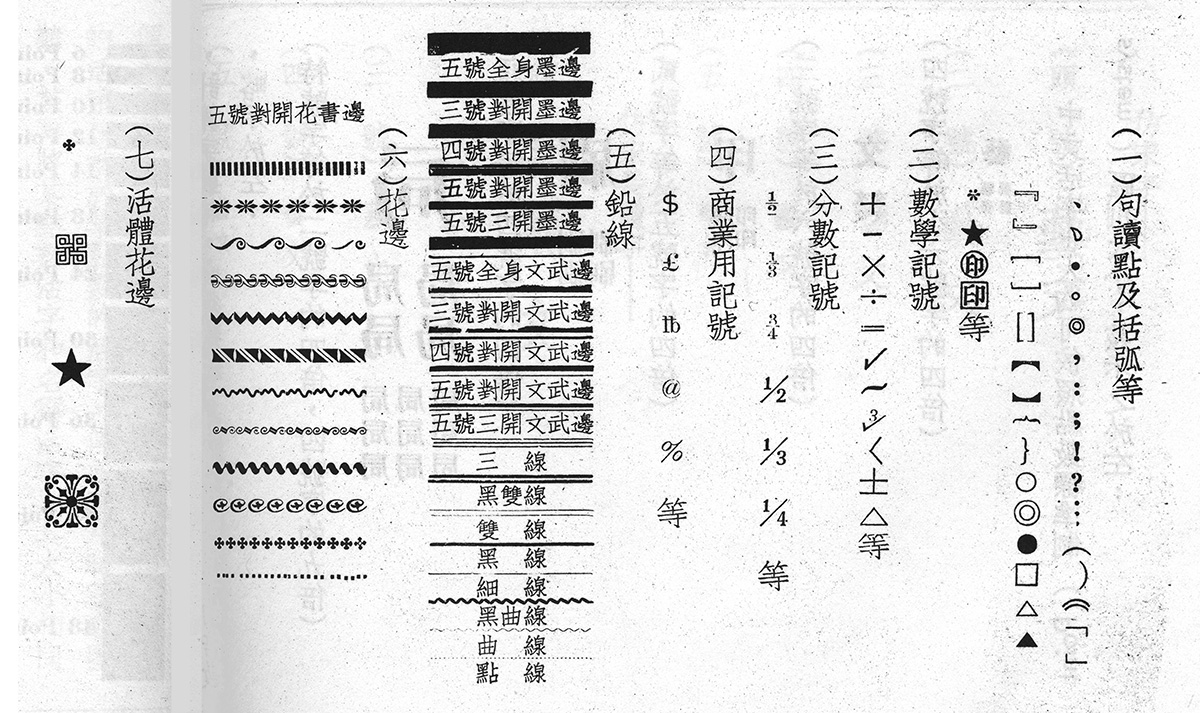
此等活体图案及花边,皆可用来装饰广告印件,使之排列整齐而美观,不独可以引人注目,也可培养阅读的时的兴趣。
三、英文活字
英文活字的大小,在点数标准制未完成以前,多附以名称而区别之:
- Ruby(英文名称)/ Agate(美国名称),相当七号字
- Nonpareil Brevier,相当六号字
- Small Pica,相当五号字
- Pica English,相当四号字
- 2-Line Brevier,相当三号字
- 2-Line Small Pica,相当二号字
- 2-Line English,相当头号字
其他在 Nonpareil 和 Brevier 之间有 Minion,在 Brevier 和 Small Pica 之间又有 Bourgeois 和 Long Primer,在 2-Line Brevier 之上,又有 Great Primer,更有最大活字。Canon 等,非常複杂,其大小以 Pica 为标准。此等旧名称至今仍沿用未废,故为广告制作者所不可不知。
英文活字以前系用 Pica 为标准,但 Pica 本身的大小,因制造所而用,所以同一名称的活字其大小因制造所的不同而不一律,欲混用甲乙二制造所的活字,遂不可能。为要免除此种不便,因而决定一基准尺寸,就是采用点数标准制(Point System )。此制有二种:一种是一七三七年法人福利挨(P.S Fournier )倡议用点数标准制为测定活字大小所用的单位,但尚有缺点;及至一七五五年法人提多(Fancois Ambroise Didot)改良此制,以法国当时施行的规尺为基础,而正确地测定一方吋的七十二分之一为 1 Point ,采用单位,即所谓提多式点数制(French Didot Point System),现在奥大利、小亚细亚地方,比利时、秘鲁、丹麦、德国、匈牙利、罗马尼亚、土耳其等国都采用此制。
另一种是美国式的点数制,即以马凯雷,斯密斯,佐尔丹公司(Mackeller Smith & Jondant Co.)所铸造的 Pica 为基础,将六个 Pica 视作一吋,以 1 Pica 分为十二点,故一吋共分为七十二点,规定以这一点为标准,英美诸国即采用此制。我国和日本的英文活字,多自英美输入,所以也可以说是采用美国式的点数制。兹将点数制的英文活字和各种字体,示之于左:
英文点数制活字
英文各种字体及其名称举要(各种字体名称,即以其本体举例)
(以上各种字体名称,各书多不一致,究竟何者可算标准名称,作者不敢肯定)
直至今日对于英文活字的称呼,或沿用旧名,或采用点数制,尚未能统一,在应用上殊感不便。因为称呼的歧异,所以我们必须知道某名称的活字相当于某点数的活字,俾于应用时不感困难。兹再将某点数活字和名称活字,其大小相同者列表于左,以供参考:
四、活字的应用
中英文活字的种类和大小,已略示于上,我们可以知道活字的体式,各有显著的不同,广告制作者可以随意从各种字体中,选取最适当者应用。活字的功用,除了借字句传达意思外,且依其大小和字体的不同,能表现出优雅、强力、美感、装严的气氛。所以活字的本身,也能予读者以种种印象。例如贵金属和宝石一类的广告,中文活字可用仿宋体和正楷体,以表现优美高尚之感,而予读者以特殊的暗示和印象;惟仿宋体微嫌无力,这是他的缺点。如用于机械一类的广告上,为要暗示正确和强力,可用粗体活字,以表示装重的气氛。对大众诉求的广告或儿童玩具的广告等,选取活字的体式,可用注音汉字或正楷字,俾易于阅读。总之,选取活字的体式,须视广告的性质择其适合者应用之。若漫然不加选择,于广告的效果上,殊有损害。
隶体、篆体、和行书活字,目前在中国还没有。(日本有之,而且用于广告上也不少)这种体式的活字,笔画既不明瞭,又不调和,所以只能用为装饰;因为不很普通你的缘故,不宜用于标题等主要文字。
使用于广告最妥当的,而且最调和的是宋体字。这种字体自报纸、杂志、书籍,以至一切印刷物;几乎无不使用它,一般读者看起来最熟惯,字画也一见判然。近年来汉文正楷活字,非常流行,因为这种字体,就是我们日常所写的楷书,其能普遍易读的原因,也就在此,在将来必占极优越的地位。宋体和正楷体字使用于无论可处,都很妥当。粗体字虽较宋体字感觉很强有力,易惹起读者的注意,但同时也有沉灪之感。所以,用粗体字排长篇的文字,徒然使广告面沉闷无生气,令人厌倦。不过因为它的注意吸引力比普通宋体字大,文章中的特别重要部份,如标题、商店名称、商品名称等若用粗体字,则更为有效。中英文字虽然不同,但在应用的原则上大致是相同的。
关于活字在应用上的问题,最重要者有下列各点:
(一)适应性
活字的使用最重要者是关于情调的研究,要能够借活字把所广告之商品或劳务的性质,暗示出某种印象不同;同时并暗示商品的品质和劳务的价值。关于这种活字的能力,许多广告学者曾作过重要的研究。
(二)易读
要使广告容易阅读,须视一切表现要素如何而定,不仅限于活字问题,且受文字文字和单语构成之性质不同的影响,而发生许多问题,简言之,有下列各点:
-
A 文字每行排的很长,使人看了讨厌。行的长条,是因活字的大小而不一定的,但如中文的六号字或五号字,每行字长逾六吋时,就不易阅读;英文字的 10 Point 至 12 Point 活字(约当中文活字的五号和小四号),每行字长逾三吋半时,也同样的难读。
-
B 若使用多种大小不同和字体各异的活字,也是不易阅读的。
-
C 组成长文时,至适当长度应分段另行起。
-
D 活字和全广告面的大小之比例,不要过大或过小。
-
E 行与行的间隔和文字与文字的间隔,不要过宽或过紧。
-
F 行间和字间不统一时,阅读起来便觉得讨厌。
(三)体裁良好
所为体裁是指活字和其他构成要素(即空白、大小、平衡、色彩、及全盘的支配等)之间特定的表现关系而言。广告上此种支配,必须适当。
(四)文字的方向
阅读中文或日文时的视线,有自上部右侧向下移动的习惯;读英文时,有自上部左侧向右移动的习惯。视线的移动,向这种方向最为容易。我们阅读下面所举的 AB 二例时,觉得 B 比 A 容易阅读,同时读起来也更迅速,这是因为借行间的线,划清文字的界限,使视线移动容易的缘故。其次,我们在日常的报纸、杂志上所看惯了的中文四号和五号活字,或英文 9 Point ,8 Point 活字,比其他活字读起来也更容易。
(五)适当的配置
要顾虑到插图和空白关系,在能保持平衡和秩序的地方,适当地配置活字,借以引起读者的注意力,而使其读竟全文。在一张广告中,如果散漫地配置活字时,徒然使已经抓住了的读者注意力,转移于他处。
(六)强势
关于活字的强势要素,是利用空白、配置、活字的适应性、大小、粗体、轮廓、线条、圈点、动人的标题,及其他许多技术上的问题等组成的。
(七)技术上的熟谙
要能体会印刷上的技术,必须和印刷者多接触,同时要实际从事校改,因为广告上图案和活字的排列,校对时格式的改正,是很重要的。比较长的文字,排成活版的地位,是不易准备估计的。关于活字的用法,不外乎经验。
欧美现时流行字体之鸟瞰
西文铅字字体大概计算起来,约有一千余种之多。但随着时代潮流和人类心理的改变,它也在新陈代谢的改变着,有些旧的字体业已淘汰,而有些新的字体却又已产出出来。然而,据我个人检查欧美书报及各类刊物的结果,现行最流行的字体也不过四五十种而已,姑就平日搜罗所得,草成成本,以实本刊。
我们首先应注意的,在这四五十种的字体中,有些字体的流行性仍在逐渐扩大,而有些则正在缩小。有悠久历史的 Sans 体,虽然样式繁多,譬如说,英、美、法、德、荷兰等过的铅字都有这种字体,但它的用途仍然方兴未艾,其中尤以 Gill Sans 体称雄一时,自五磅半至七十二磅一应俱全。能和 Sans 体颉颃的,当推 Erbar 体、Cable 体、Futura 体等三种;Bernard Gothic 体、Granby 体和 Guilford 体的用途亦广。其次,Vogue 体、Metro 体和 Tempo 体也有庞大的销路。
Sans-serif 体前此曾一度不被人采用,最近却又风行一时,这不能不称为异数。Egyptian 体,在欧美铅字字体中,最近才渐有其稳固的地位;而 Rockwell 体、Cairo 体和 Karnak 体,Luxor 体、Beton 体和 Stymie 体,以及 Scarab 体和 Memphis 体等,也都是最近数年才展露头角的。
还有一些字体,也受到许多人们的欢迎,字体较细的为:Bernhard Cursive 体、Gillies Gothic Light 体、Madonna Bold 体、Mayfair 体和 Trafton 体 。
字体较粗的,如:Bernhard Brush 体、Gillies Gothic Bold 体、Samson 体、Glenmoy 体和 Holla 体。
以上所述,都是多年以前发明的字体。至于最近一二年发明的字体,有若干种在最近的将来的也许会蓬勃一时。例如:德国 Penflow 体和 Pentape 体、Sketch 体和 Allegro 体、Cartoon 体;美国的 Kaufmann 体分为 Medium 和 Bold 两种,此外还有 Hauser Script 体。这些字体的特点,在于笔书清晰,易于辨认。
最近发明的缮写体,有 Marina 体,系一种铜制的字。Diane 体和 Flex 体则为美国最近发明的两种缮写体。
最近发明的细长体,有德国的 Bayer 体,是 Edeh 体和 Bodini 体二者的折衷体。美国新发明的,Slim Black 体、Bodoni Companile 体、Onyx 体、Empire 体等。
异军突起的字体有 Albertus 体和 Offenbach 体,它们并不脱胎于任何一种旧有的字体。
本文所附载的字体样本,搜罗尚不齐备,容俟将来有机会时,补行披露。